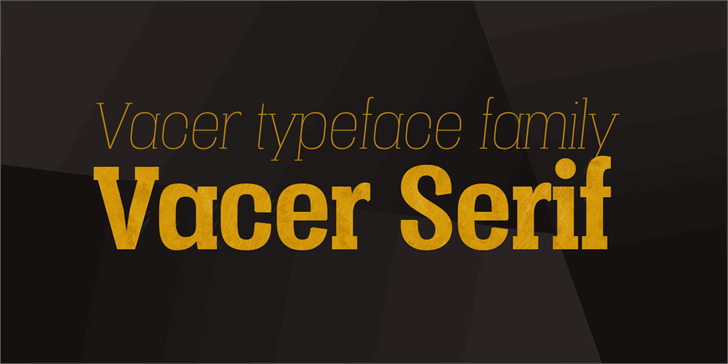
Vacer Serif é uma elegante fonte serif que adiciona um toque sofisticado a qualquer projeto gráfico. Desenvolvida pelo designer Hamilton, esta fonte oferece uma ótima combinação de simetria e riqueza tipográfica. Suas linhas arredondadas criam uma sensação calma e confortável para o olho, ideal para textos em cartazes ou portfólio empresarial. A Vacer Serif é perfeita para criar um visual elegante e profissional que destacará seu trabalho gráfico. Para os designers interessados, a fonte está disponível para compra no site da MansGreback.com. O acesso direto à essa font poderia trazer uma nova dimensão ao design das suas criações, tornando-a ainda mais única e atemporal. Engane-se se acredita que Vacer Serif é apenas uma fonte mais; ela é um diferencial para qualquer projeto visual.